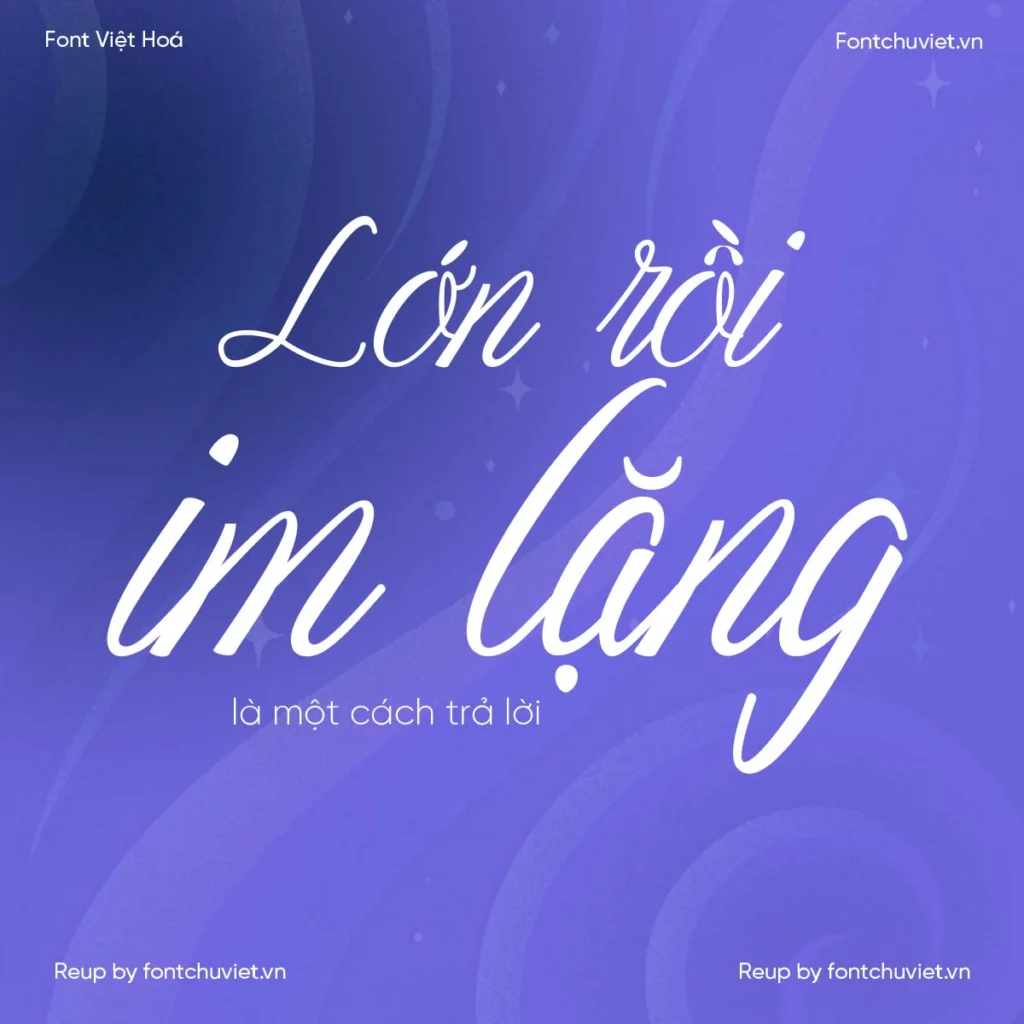
Font VL Araura là một trong những font chữ được sử dụng rộng rãi trong thiết kế hiện nay. Với độ dày đậm hợp lý, Font VL Araura mang lại vẻ đẹp chuyên nghiệp cho thiết kế của bạn. Tuy nhiên, nhiều người vẫn chưa biết cách sử dụng Font VL Araura một cách hiệu quả.
Ứng Dụng Của Font VL Araura
Font VL Araura thường được sử dụng cho thiết kế tiêu đề và nội dung chính. Với kiểu dáng viết tay độc đáo, Font VL Araura mang lại sự sáng tạo và thu hút cho thiết kế của bạn.
Cách Sử Dụng Font VL Araura Hiệu Quả
Lựa Chọn Kích Cỡ Phù Hợp
Kích cỡ của font chữ là một yếu tố quan trọng trong thiết kế. Để sử dụng Font VL Araura hiệu quả, bạn cần lựa chọn kích cỡ phù hợp với thiết kế của mình.
Sử Dụng Màu Sắc Phù Hợp
Màu sắc cũng là một yếu tố quan trọng trong thiết kế. Để sử dụng Font VL Araura hiệu quả, bạn cần lựa chọn màu sắc phù hợp với thiết kế của mình.
Lợi Ích Của Font VL Araura
Font VL Araura mang lại nhiều lợi ích cho thiết kế của bạn. Với độ dày đậm hợp lý, Font VL Araura mang lại vẻ đẹp chuyên nghiệp cho thiết kế của bạn.
Kết Luận
Font VL Araura là một lựa chọn hoàn hảo cho thiết kế tiêu đề và nội dung chính. Với độ dày đậm hợp lý, Font VL Araura mang lại vẻ đẹp chuyên nghiệp cho thiết kế của bạn. Hãy thử sử dụng Font VL Araura trong thiết kế của bạn ngay hôm nay!
- Font VL Araura là font chữ phù hợp cho thiết kế tiêu đề và nội dung chính
- Font VL Araura mang lại vẻ đẹp chuyên nghiệp cho thiết kế của bạn
- Font VL Araura có độ dày đậm hợp lý